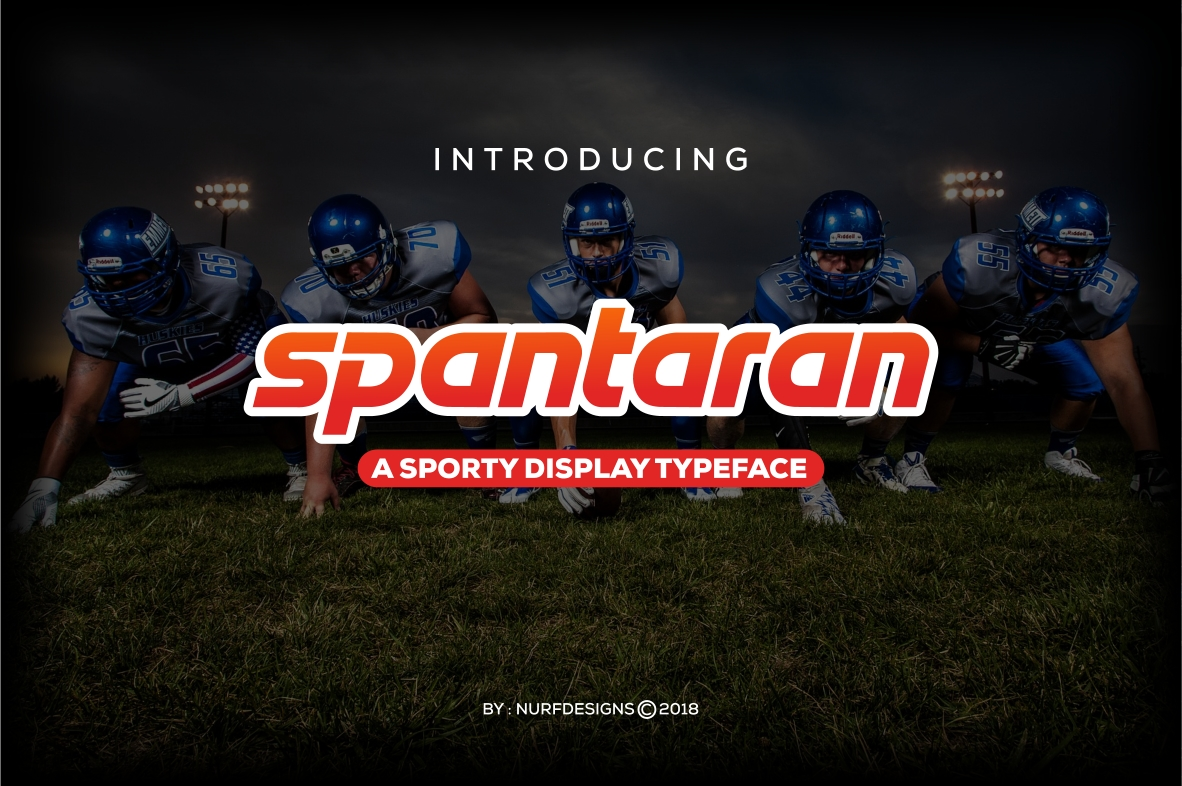
Spantaran Typeface – Download Grátis
Spantaran Typeface é uma tipografia para aparição que traz estilo esportivo e perfeita para uso em logomarcas, títulos, nomes dos jogadores estampados nas camisas, além de outros aplicativos. Sujeitado a caracteres itálicos e negritos, Spantaran é projetada para dar um forte impacto visual, tornando-a uma escolha ideal para o design gráfico atual. Seu caráter esportivo, combinado com elementos distintos e modernos da família de tipografias, cria uma identidade única que promete destacar qualquer peça de arte ou projeto em que for usada. Para designers buscando um toque vibrante e emocionante para seus projetos, Spantaran Typeface é a escolha perfeita.
Designer: nurfdesigns